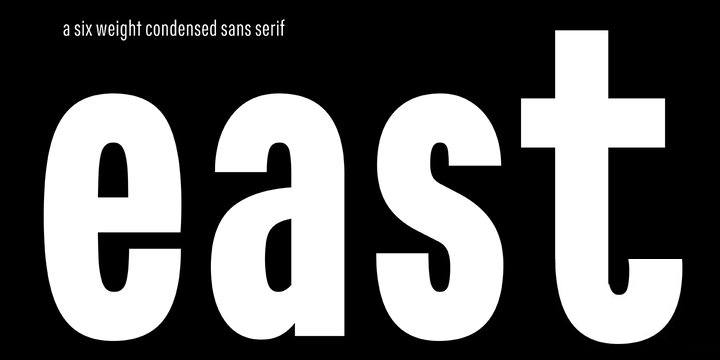
East - это конденсированный шрифт без засечек. Он имеет шесть начертаний от Light до Extra Bold. Имеется также переменный шрифт.
Четкость и универсальность делают East хорошим выбором для дизайна приложений, брендинга, названий фильмов, информации, упаковок, плакатов и публикаций. Он простой, дружелюбный и уверенный.
Его сжатый дизайн позволяет легко разместить текст в ограниченном пространстве. Легкий шрифт обладает отличной четкостью, что облегчает чтение даже при небольших размерах. Начертание Extra Bold привлекает внимание в качестве заголовка или крупного основного текста.
Название "Восток" должно вызывать в памяти оптимизм, движение, путешествия и восход солнца. Оно вне времени и актуально, с легкой ностальгией - навеяно очаровательными одноразовыми засечками на ранних джазовых альбомах, названиях фильмов, газетах и дорожных указателях.
East обладает многими возможностями OpenType (см. слайды). Он предлагает восемь стилистических наборов. С их помощью можно быстро изменять большие объемы текста. В нем есть набор для одноэтажной буквы "а" для более простых текстур абзацев, а также набор для крючковатых букв (f, j, l, r, t, y) для более теплой и игривой индивидуальности. Прописные буквы I и 1 с засечками, а также косой ноль обеспечивают лучшую читаемость, когда это необходимо. Также имеются наборы для фигурного немецкого эсцетта, выровненных по центру знаков препинания для испанского языка и рельефного двоеточия. Другие альтернативы OpenType включают: три различных прописных немецких эсцетта, конический восклицательный знак, альтернативу 4, стандартные лигатуры, произвольные лигатуры, коническую звездочку и набор пуль (круглые, квадратные и ромбовидные).
Он также содержит предварительно построенные вертикально сложенные дроби. Для распространенных дробей (четверть, половина и три четверти, проценты, тысяча) предлагаются диагонально построенные альтернативы.
Поддерживаются западные и центрально-европейские языки, а также другие письменные языки на основе латинского алфавита (проверьте свой язык). Помимо общепринятых греческих математических глифов и математических символов есть и другие.
Особенностью переменного шрифта является то, что все веса шрифта находятся в одном файле, и вы можете постепенно регулировать ширину и наклон курсива между Light (300) и ExtraBold (800). Эти изменения обычно выполняются с помощью ползунковых регуляторов в палитре шрифтов/типов программного обеспечения. Переменные шрифты также имеют меньший размер файла, что благоприятно сказывается на производительности как веб-приложений, так и программного обеспечения.